对很多普通读者来说,“中华字库”还是一个陌生的名字,但在业界与学界,它的启动却吸引了众多关注。借用新闻出版总署副署长孙寿山的话说,这是引领中华文化步入信息化、数字化时代,提高中国文化软实力的一项重要举措。这样一个使命重大的“字库”,究竟有着怎样的玄机?近日,我走访了新闻出版总署中华字库总体组专职副组长张力伟,他为我们揭开了神秘面纱,我们一起走进“中华字库”的大世界。
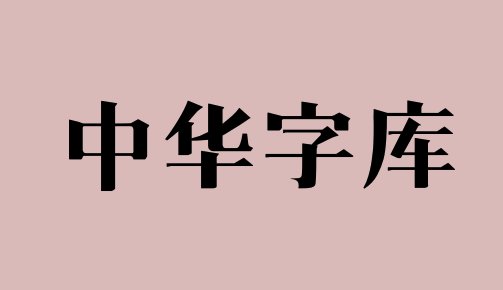
收集字符,“文理”结合
为满足文字及其他书面符号在计算机上的表示、传输、存储等种种要求,需要对文字和符号予以编码,并用符号的位序将它们组织为一个字符集。这一编码字符集,俗称“字库”。简单地说,“中华字库”就是一个收纳了中国古今的汉字及少数民族文字形体的庞大编码字符集。对于这项国家重大工程,《国家“十一五”时期文化发展规划纲要》作了如下表述:“中华字库”工程是要“建立全部汉字及少数民族文字的编码和主要字体字符库。重点研发汉字的编码体系、输入、输出、存储、传输以及兼容等关键技术。”
这一简洁表述的背后,其实包含了很多复杂的内容。张力伟说,这项工程不是只简单地收集文字进行编码整理。一方面,我们要从数千年流传下来的文字载体中,尽可能全面地搜集汇聚古今各种文字形体,在所出现过的实际文本原形图像的基础上,确定历史演变,整理字际关系等等,对学术质量的要求很高。为此,工程聘请中国文字学会第一任会长,在文字学界极具威信的裘锡圭教授担任首席专家,会同文字学界的许多专家参与研发;另一方面,这么庞大的整理工作,若像传统的那样人工搜集、抄录,将不可避免地存在人为错误多、记录信息量少等问题。“中华字库”工程将以现代信息技术作支撑,通过有效的人机结合,让计算机巨大的存储能力和便捷的检索类聚能力为文字专家的专业研究服务,利用机器来放大和倍增专家的工作效力。工程决定由中国科学院软件研究所等软件研究的精锐部队来承担工程的技术研发,为工程的开展提供技术支撑。
由此看来,“中华字库”不仅关乎学术,还关乎技术,“文理”结合十分紧密。这项工程是在对文字学深入研究的基础上,研究各种文字收集、筛选、整理、对比和认同的方法与原则;充分利用先进的数字化技术,开发相应的软件工具,在统一的数字化平台上,建立人—机结合的文字收集、整理、筛选、比对和认同的操作与管理流程。中华字库工程不仅会全面收集整理全部汉字、建立汉字的主要字体字符库,还会尽可能全面地收集整理少数民族文字并为其建立主要字体字符库;不仅要提交古今汉字及少数民族文字的国家编码、国际编码标准提案,还要为中华字库在不同领域的应用提供支撑工具与环境、实现中华字库在互联网的在线发布,并且建成面向用户的动态补字系统。在数字化服务方面,可谓是一应俱全。
已有整理,难应所需
也许你会说:全面整理文字,有必要么?咱们不是有《汉语大字典》了么?其实不然。据了解,1985年开始分卷定稿的《汉语大字典》共收列楷书汉字6万左右,已可以算是中国汉字的一次全面梳理,亦是当时条件下最优秀的汉字科研成果。然而,对于我国浩瀚的文献档案中的实际用字,对于不同时代不同地域社会生活中的实际用字,当时还不具备全面调查的手段和条件;而且该书以楷书文字为主,至于甲骨文、金文、小篆和隶书等古文字形体,并未全面整理,只在楷书单字条目下收录了有代表性的一部分,用以反映形体演变关系。除了汉字,我国还有许多少数民族文字,包括不少海外收藏的少数民族古文献文字,没有被整理出来。研发成功后的中华字库,不仅将包括针对社会应用的实用楷书字表,也将形成楷书总字表,还将有一个包含古文字的整体的汉字字表,到了最后阶段,少数民族文字也将被整合进来,最终形成一个完整有序的,有着内在联系的大型“中华字库”文字资源库。
与之前已有的文字整理工作相比,“中华字库”的优势还在于,其文字整理将面向出版及网络数字化需求。也许有人会问,咱们的电脑不是已经能方便地输入汉字了么?是,可能你觉得够用了,可是像派出所负责户籍管理的警察或者街道办事处负责人口普查的同志等肯定会给出不一样的回答。目前,我国的数字化建设正遭遇瓶颈。小到自然资源、地名、人口等清理普查,大至国家的经济、地理空间等战略性、基础性的信息库建设,还有公安、民政、金融、保险、海关、民航等行业的信息服务与监管存在很大的用字缺口。我国文字种类繁多且字量庞大,特别是汉字,内部关系又异常复杂,现有的计算机字库,无论是国家标准还是国际标准,都存在收字不全、字际关系不清等问题。少数民族文字缺口更大,除几种主要少数民族的文字外,许多甚至还没有编码。这些问题都严重影响了国家数字化建设的方方面面,也在直接或间接地影响着人们的生活。建设“中华字库”工程,就是要彻底解决这一瓶颈问题,全面推动我国的数字化建设。
任务重大,远景诱人
据了解,与“中华字库”类似的工作,世界各国都在做。欧美一些国家甚至把当地的土著文字、古代表意文字等一些极为罕用甚至早已死亡的文字,都加入了国际编码,使本国本民族的历史文化得以在网络上流传,从而展示出国家的文化实力。
我国的古汉字与现代文字一脉相承,加上有大量出土文物支撑,整合现有的研究成果,进行编码、制作字库,就更显得有必要了。包括古老的汉字及其他少数民族文字在内的中华文字,是中华文化的传承“双手”。我国历代的盛世,都曾对各民族的古今文字进行过广泛的搜集与整理,以更好地传承各种文献。现在,随着中国在国际上的影响力越来越大,中华文化走向世界已成为潮流。在当今世界数字化、信息化的发展大趋势下,未来人们的生活会越来越多地与数字化相融。中国文化要“传下来”、“走出去”,当然要依靠数字技术和网络平台才行。我们还要将古代的、现代的各种图书文献逐步数字化,使中华文明得以永久保存,并且广泛传播,这也是历史和现实的一项非常急迫的重大任务。
“中华字库”工程的设想,就是新闻出版总署在这样的背景下,于2006年提出来的。国家对这个项目非常重视,先后将其列入《国家“十一五”时期文化发展规划纲要》和国家《文化产业振兴规划》。工程由新闻出版总署重大科技工程项目领导小组办公室负责总指导,以中国出版集团公司为牵头单位,成立了工程总体组,负责工程建设的整体管理和组织实施。除首席专家裘锡圭教授之外,总体组还从各参与单位抽调,或聘请总体组单位外的技术专家、管理专家等,组建起项目的技术团队,以承担总体组的各项工作。经过几年的精心筹备,工程目前已正式进入实质性研发阶段,计划五年完成。
审定过“中华字库”研发方案的专家说,工程是比秦始皇统一汉字规模更大的中华文字整理工程,必将对中国乃至世界文明的历史产生重大而深远的影响。